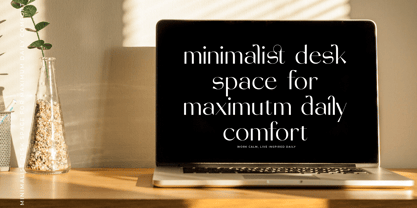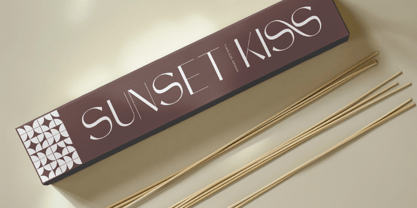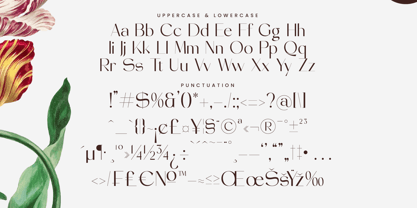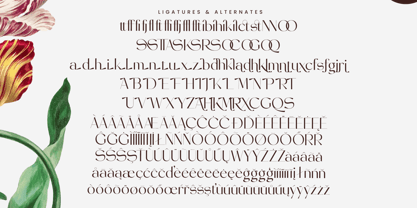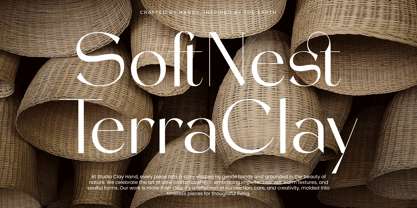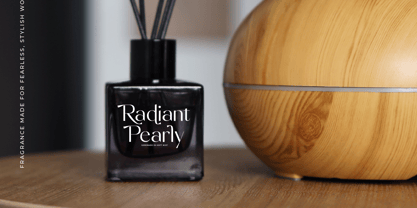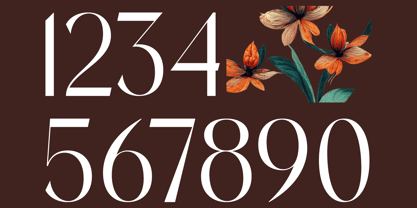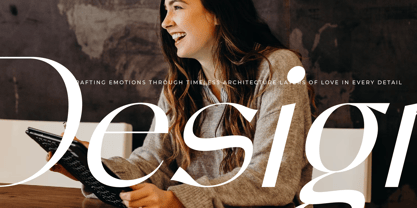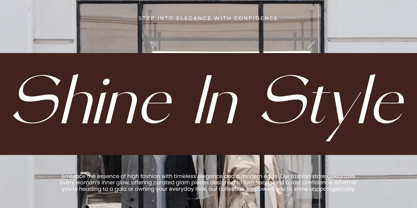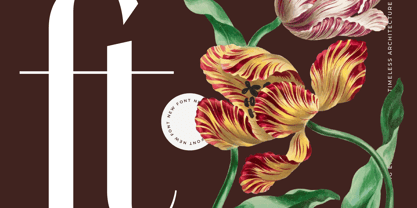
Stogne Gesture
La familia tipográfica Stogne Gesture fue diseñada por Heru Utama Putra y publicada por Timelesstype Studio. Stogne Gesture contiene 2 estilos y opciones de paquete familiar.
Stogne Gesture - Modern Sans Serif Font , from Timelesstype , Suitable for any projects such as: logos, branding projects, homeware designs, product packaging, mugs, quotes, posters, shopping bags, t-shirts, book covers, name card, invitation cards, greeting cards, label, photography, watermark, special events, and all your other luxury and beautiful projects that need a Luxury Serif taste.